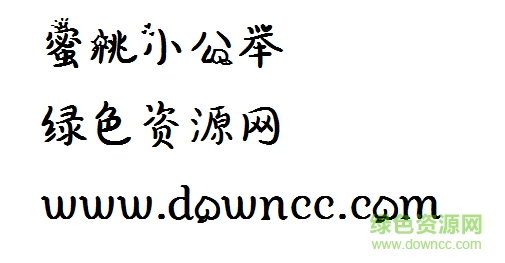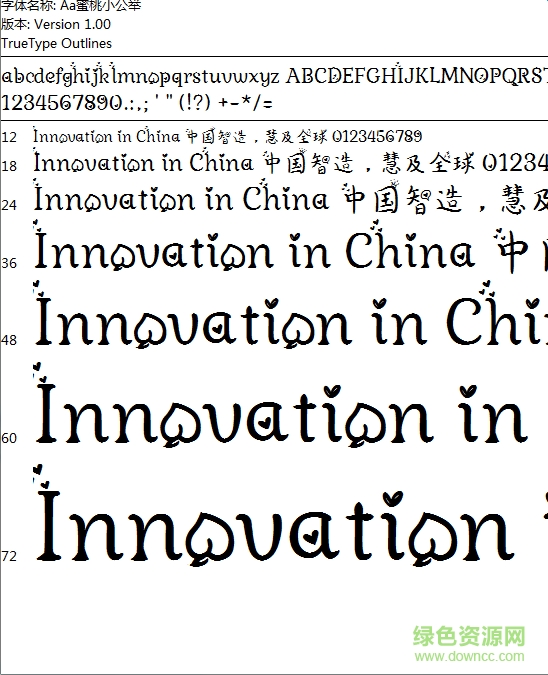
蜜桃小公舉字體是一款可愛風(fēng)格的字體軟件,字體帶愛心圖案點(diǎn)綴,十分可愛呆萌,深受廣大女生喜愛,更多好看的字體下載盡在綠色資源網(wǎng)!
蜜桃小公舉字體是一款可愛中文字體,該字體筆畫細(xì)膩,大字效果突出且引人注目;并且最大程度還原作者書寫字形,細(xì)節(jié)表現(xiàn)完整,且字庫完整,可以廣泛應(yīng)用于名片設(shè)計(jì)、新聞媒體、宣傳海報(bào)、ppt、影視制作以及內(nèi)容用字等領(lǐng)域。
該字體屬于非常可愛迷人的小清新風(fēng)格,字體筆畫優(yōu)雅大方,整體效果十分好看時(shí)尚,感興趣的朋友歡迎免費(fèi)下載使用!